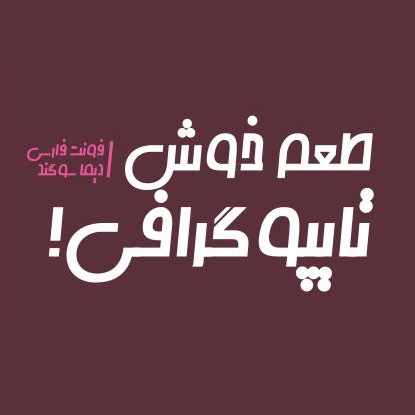
دیما سوگند
فونت زیبای رایگان دیما سوگند
فونت سوگند یک فونت فارسی فانتزی و جذاب است که برای خط فارسی توسط حسین تقی‌زاده طراحی شده است. موارد کاربری آن را می‌توان هرجایی که باید احساس خوشایندی منتقل شود، درنظر گرفت. موضوعاتی نظیر: بازی، سرگرمی، مواد غذایی، خدمات یا تبلیغات. فونت سوگند دارای استایل توخالی (Outline) و ترکیبی منسجم می‌باشد که در اندازه های بزرگ و سرتیترها به آن ظاهری چشم‌گیر بخشیده است. همچنین به دلیل ضخامت یکسان خطوط و و تناسبات دقیق در اندازه‌های کوچک هم برای چاپ و روی صفحه نمایش از وضوح خوبی برخوردار می‌باشد. در طراحی این فونت سعی شده حروف با بیشترین تراکم کنار هم قرار بگیرند تا کلمات ترکیبی یکپارچه‌تر داشته باشند. در واقع فواصل بین دندانه‌ها به صفر رسیده است. همچنین کوتاه بودن پایین و بالای خطوط کرسی از ویژگی‌های مثبت آن می‌باشد. فونت سوگند برخلاف دیگر فونت‌های فارسی در سبک Outline، تلاشی‌ست برای ارایه یک فونت اصیل و مورد استفاده در تایپوگرافی حرفه‌ای.
Dima Sogand is a Persian font designed in Regular style by Hossein Taghizadeh and Edited by R.Balvardi.